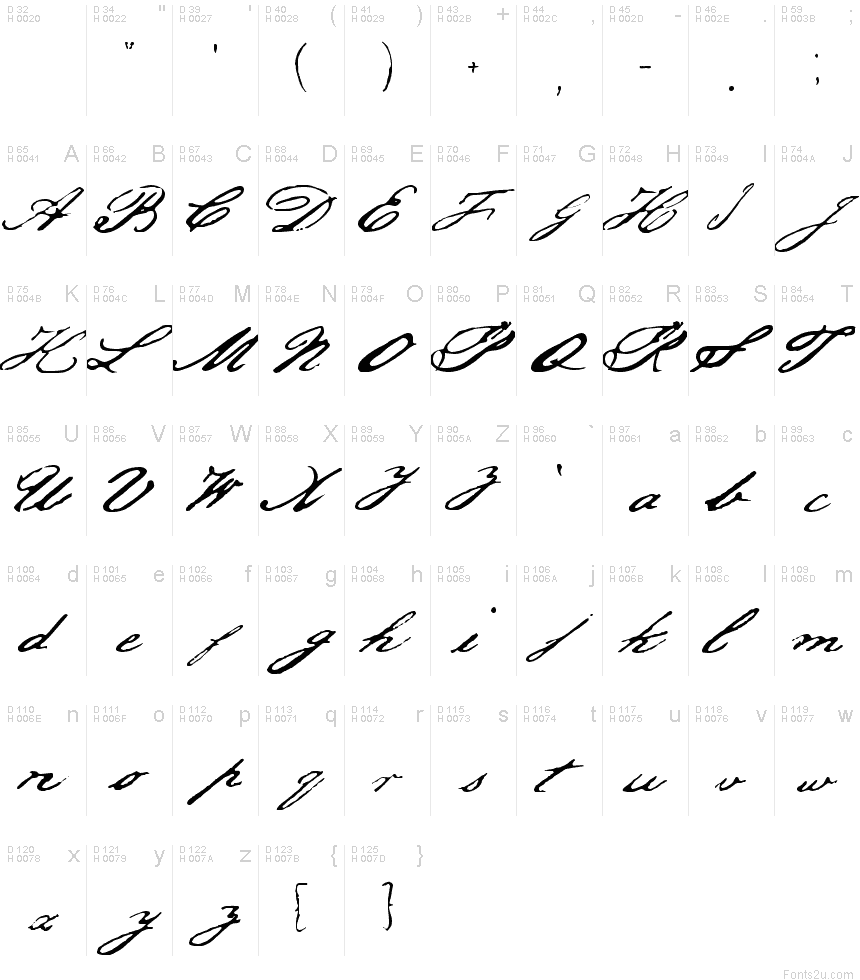
Krój Jefferson od Snatchsoft to darmowe, odręczne pismo typu script, które wygląda, jakby zostało wydrapane na papierze piórem wiecznym pełnym atramentu. Litery mocno pochylają się na stronie, z długimi, zdecydowanymi pociągnięciami i atramentowymi nakładkami, które bardziej przypominają osobisty podpis niż zwykłe pismo odręczne. Lekko surowa, jakby skserowana krawędź dodaje mu odrobinę buntu w połączeniu z elegancją dawnych lat.
Dzięki Jefferson Twój tekst natychmiast nabiera charakteru śmiałego autografu lub dramatycznego podpisu, co świetnie sprawdza się w logotypach, personal brandingu, podpisach, okładkach albumów, plakatach i cytatach. Ten darmowy font najlepiej prezentuje się w dużych nagłówkach, gdzie jego zamaszyste krzywe mogą w pełni wybrzmieć, podczas gdy tekst główny warto zestawić z prostym krojem bezszeryfowym dla lepszej czytelności. Stosuj Jefferson w dużym rozmiarze, z odpowiednim światłem i w krótkich liniach, aby pozwolić jego intensywnemu, odręcznemu stylowi mówić samemu za siebie.